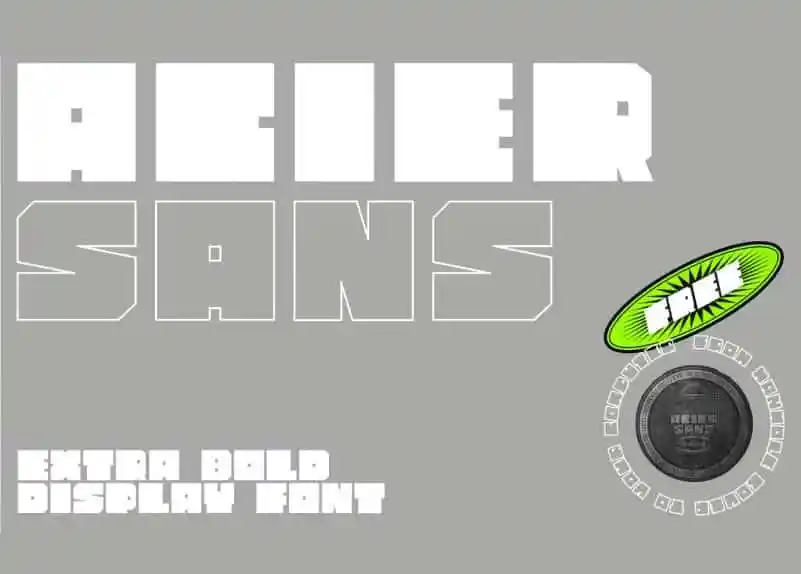
Acier Sans Display Font – Fonte Grátis
Acier Sans Display Font
A Acier Sans Display Font é uma família de tipos de grande impacto, projetada para quem precisa destacar sua marca ou conteúdo em projetos visuais intrigantes e inovadores. Feita pelo designer Calixte Patissier, essa fonte está ideal para qualquer projeto que seja acentuadamente visual e chamativo. Com seu design baseado em grade, é fácil de alinhar e manter a simetria necessária para garantir um resultado profissional. Ideal tanto para aplicativos digitais quanto para impressão, a Acier Sans Display Font é perfeita para quem busca uma identidade visual moderna e forte, que ressalta entre o caos da informação visual atual. Para aqueles que buscam algo marcante no design de seu site ou em sua próxima campanha publicitária, esta fonte pode ser a solução ideal.